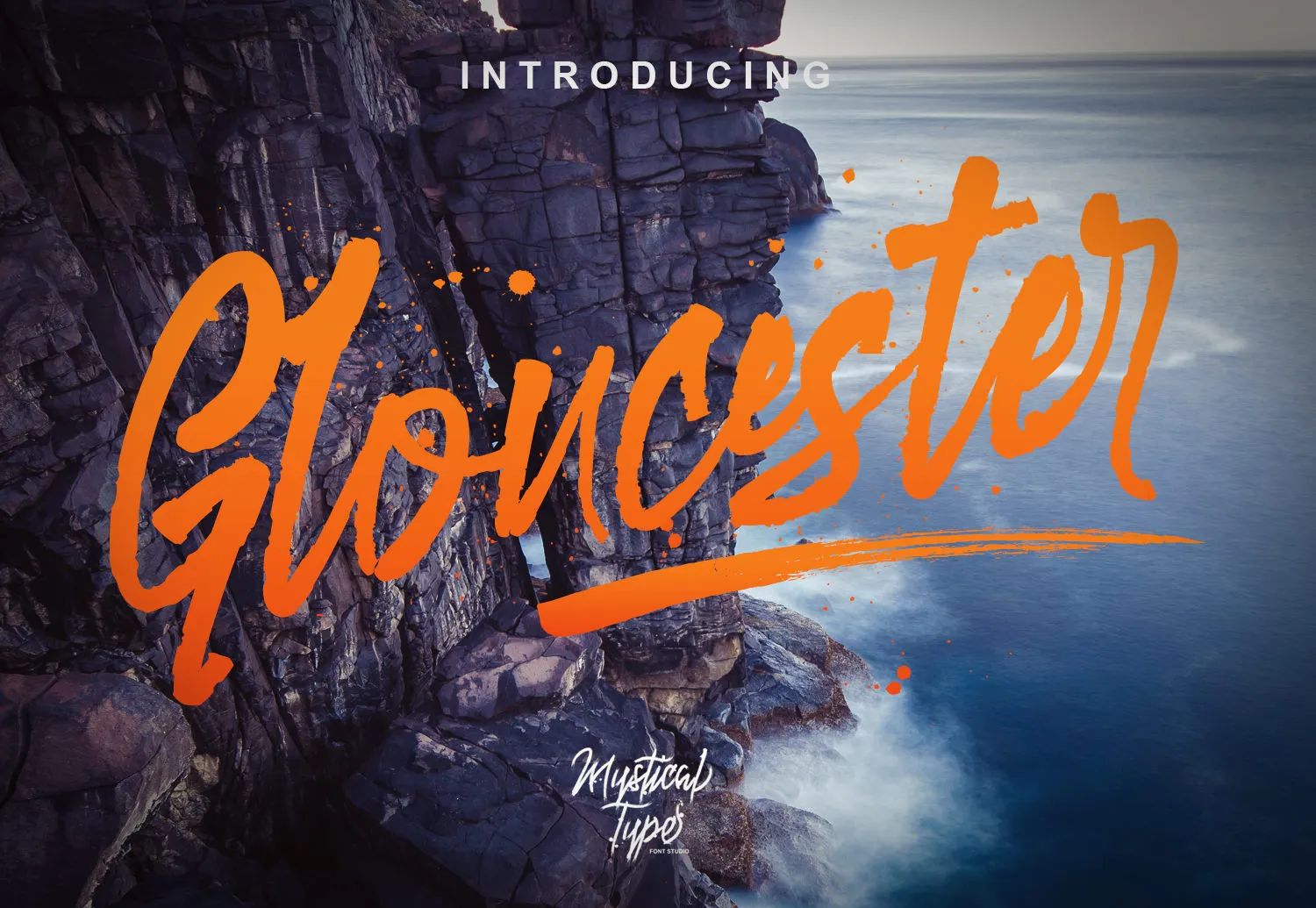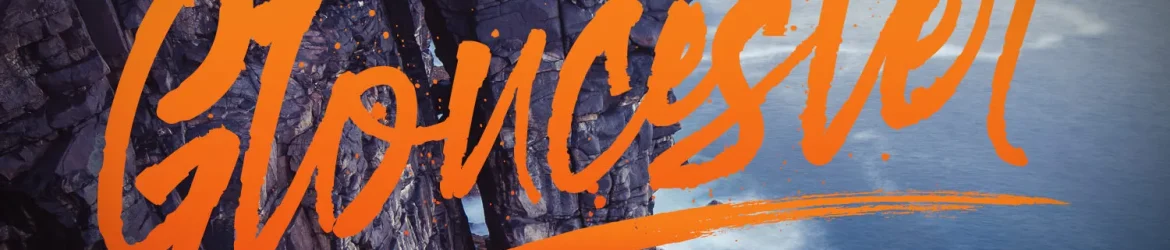
Aproveite a beleza única do Gloucester Script Font na sua próxima criação! Desenvolvido pela M.0Type, este novo tipo abraçado e autêntico transmite um encanto único para os designers de tipos. Introduzido como uma escolha excepcional entre as fontes script, o Gloucester traz vida às suas ideias com seu design refinado e influenciado por tendências modernas. Este tipo foi projetado meticulosamente em estilo de traço ao vivo, garantindo um resultado fluido e natural. Além disso, a M.0Type oferece-lhe uma opção complementar perfeita para sua fonte principal – o Gloucester Marker Font – que é perfeito para trabalhos como logotipos, citações escritas à mão, embalagens de produtos, títulos e cartazes. O conjunto extra de swashes adicionais também traz um toque especial à sua arte final. Gloucester Script oferece uma experiência sem igual, sendo especialmente adequado para aplicativos como logotipos, mensagens em estilo escrevendo à mão, embalagens de produtos, cabeçalhos e cartazes, peças de mídia social e até mesmo cards de agradecimento. Ele é perfeito para qualquer projeto que você esteja iniciando, oferecendo uma fonte única que adicionará um toque especial à sua criação.